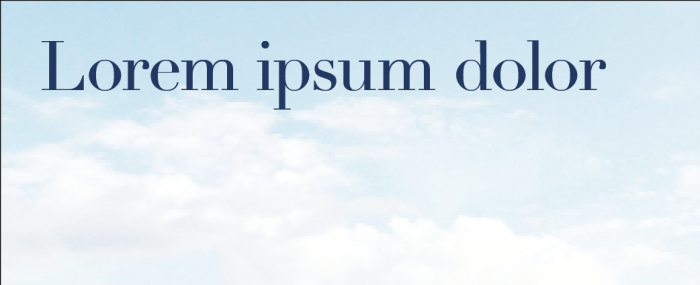
elegante feine Serifenschrift gesucht
Ich bin auf der Suche nach einer Serifenschrift, die federleicht und superelegant daherkommt.
Sie soll an ein Spa oder Resort erinnern.
Bisher fällt mir nur die Didot ein, aber die geht mir noch nicht weit genug:
Oder falls ihr noch andere Vorschläge für Spa- oder Resortschriften habt (Grotesk oder Handschrift), immer her damit.
Die Guadalupe finde ich super, genau so etwas habe ich gesucht.
Habe mich nun aber doch für die Aire Light Pro entschieden. Die ist zwar noch ein wenig verspielter, passt aber wegen ihrer wellenartigen Elemente für Spa-Headlines perfekt.